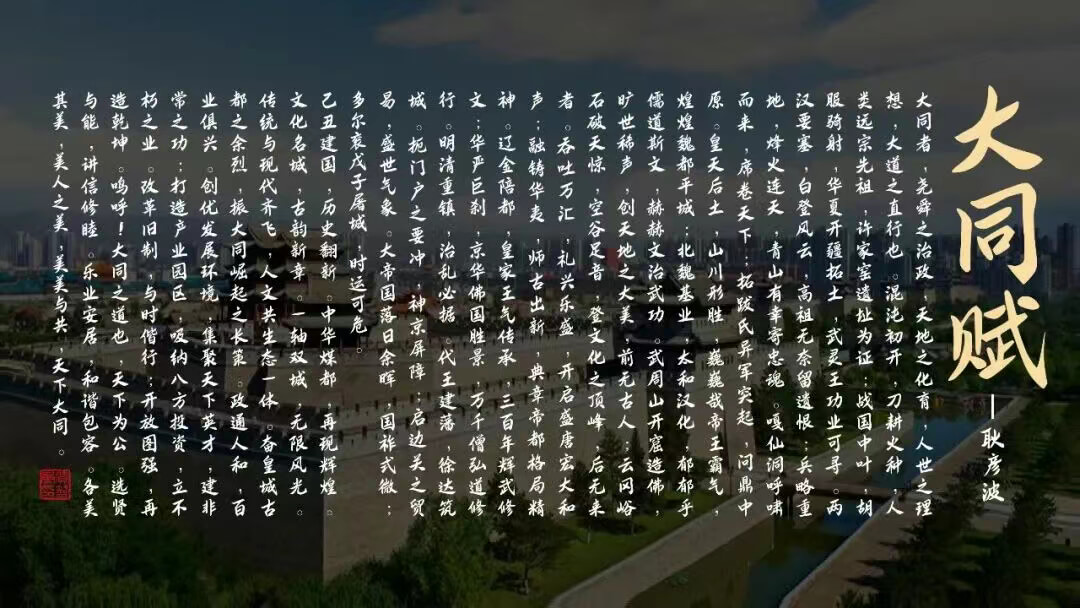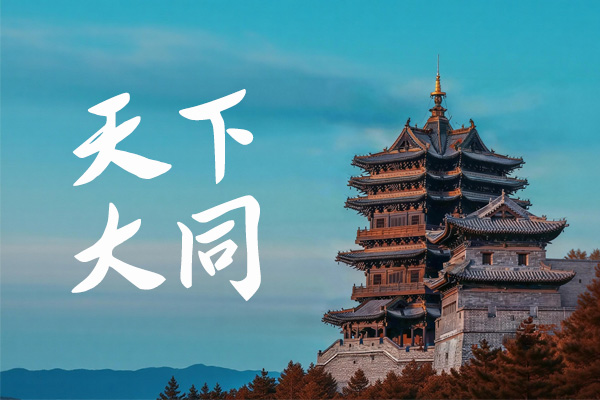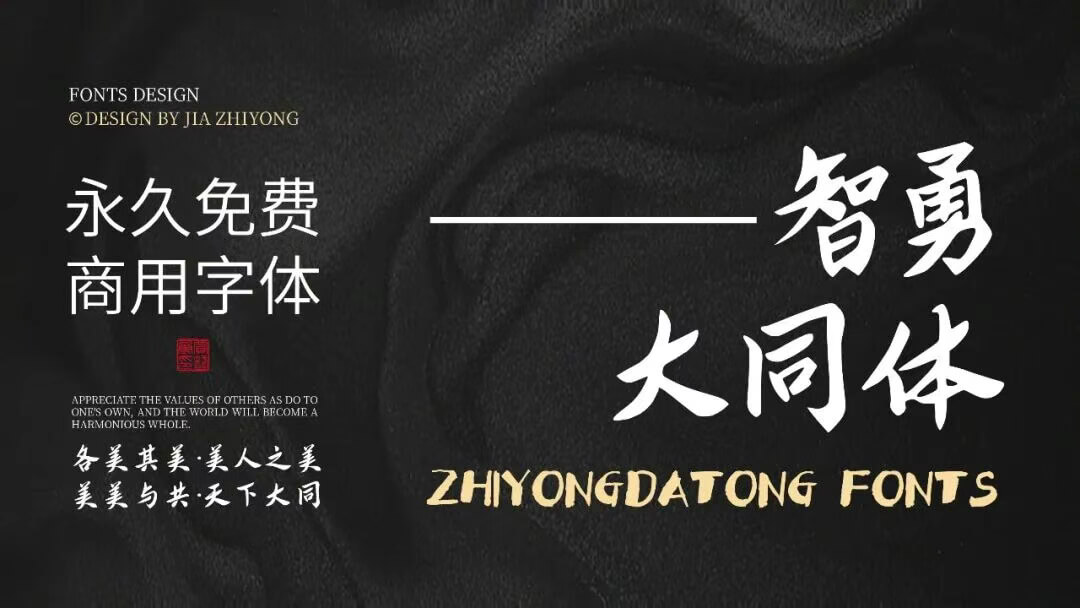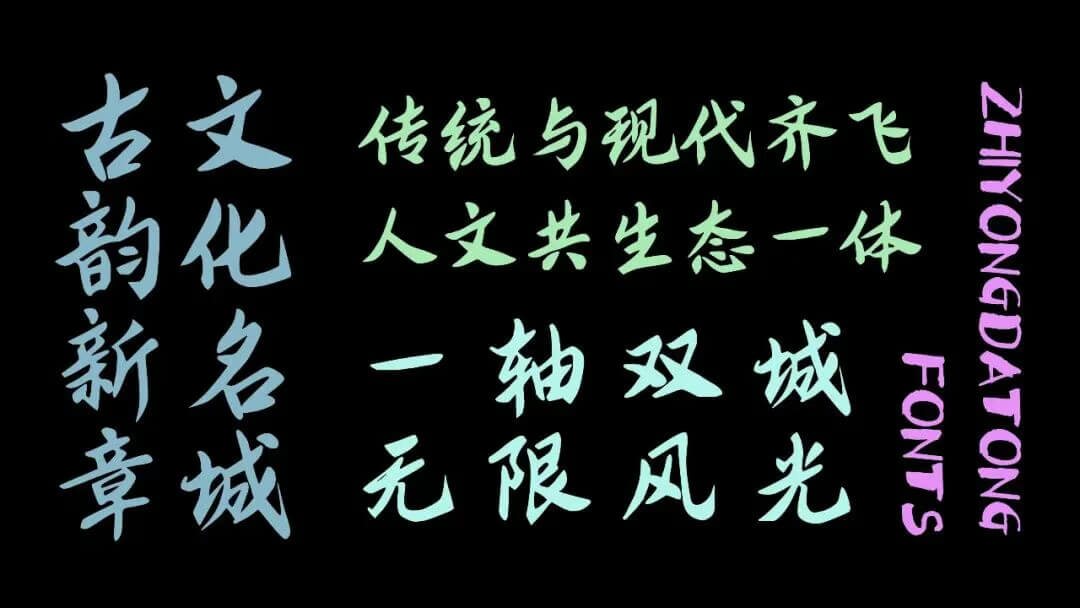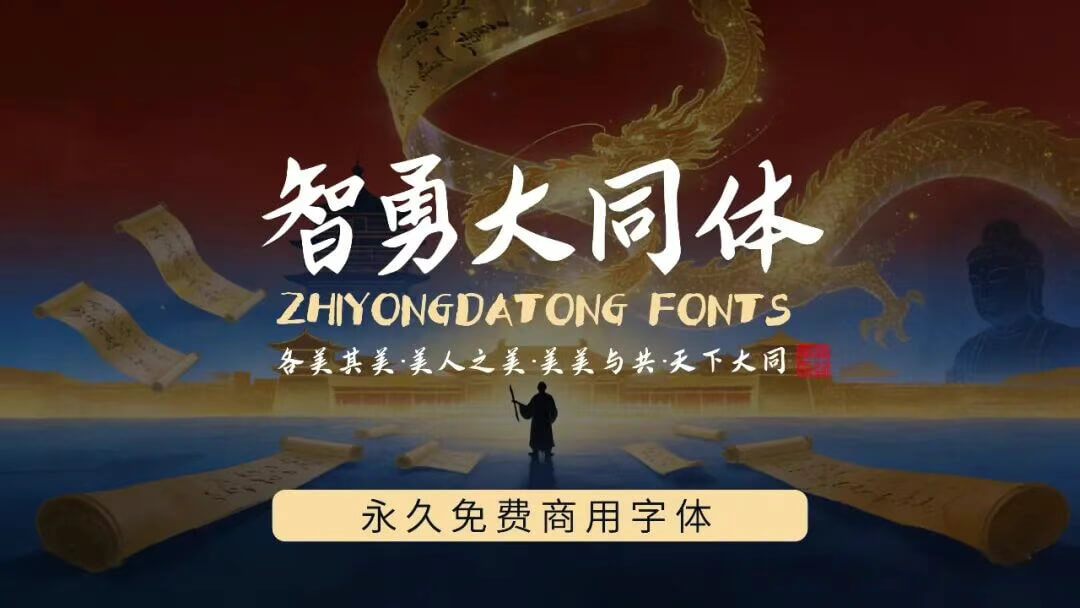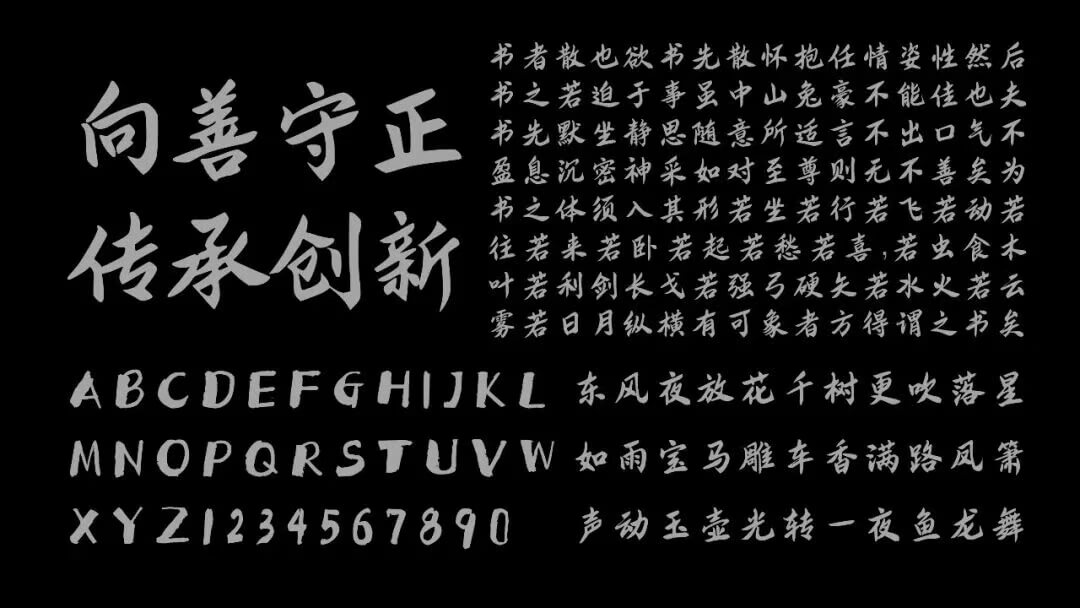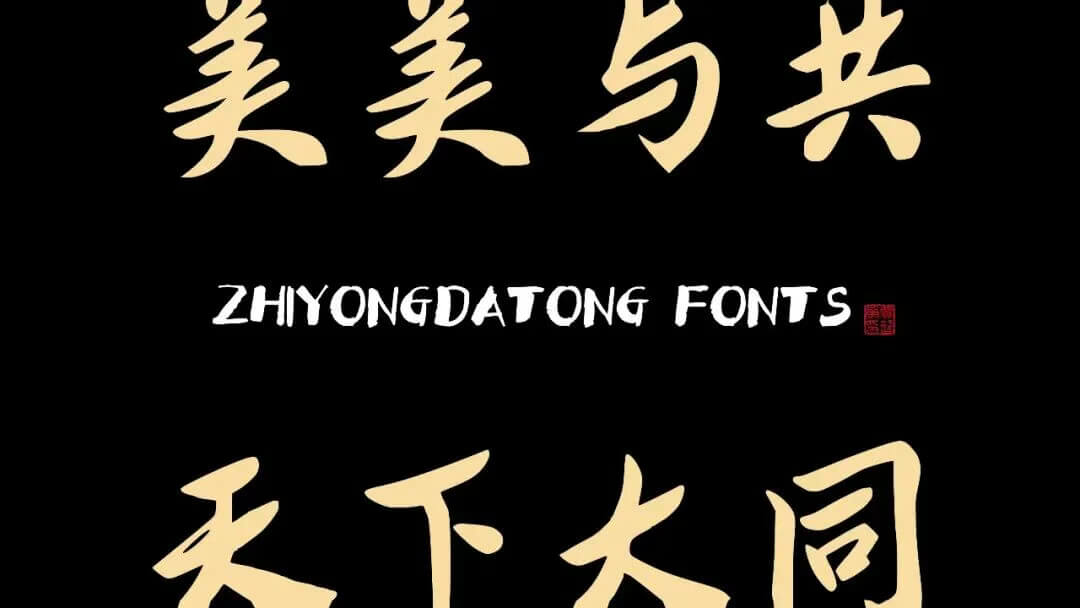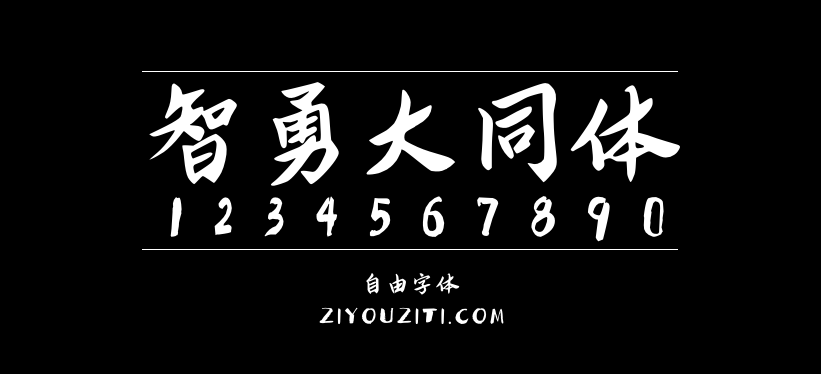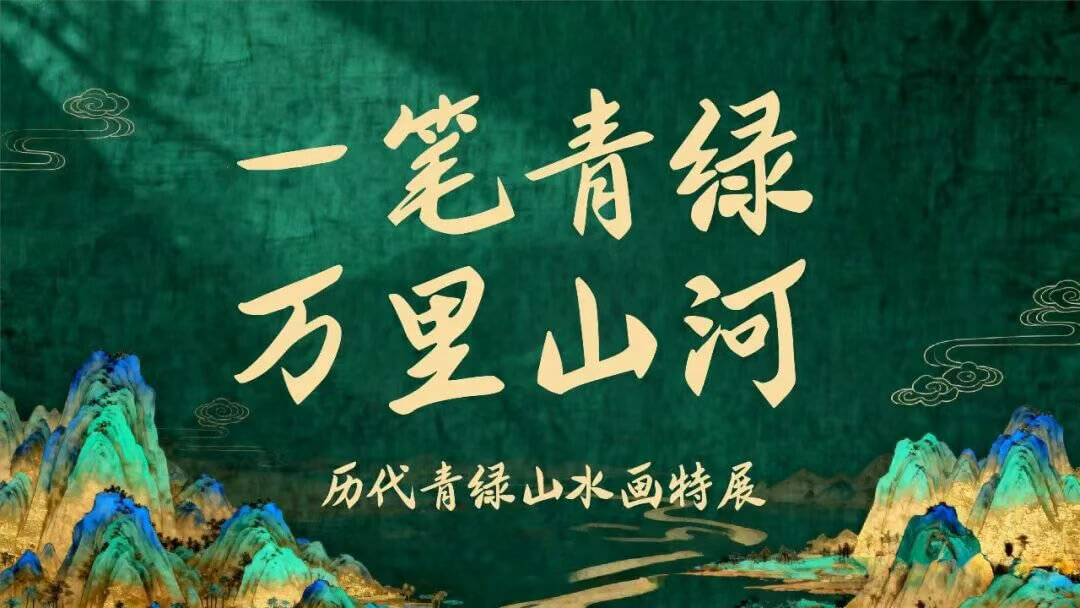
智勇大同体
智勇大同体是设计师贾智勇(智勇造字)创作并推出的第四款免费商用字体,前面三款字体分别是:
一个普通的午后,智勇用毛笔写下第一个字型。那一刻,作者没想到这会成为一场长达两年多的字体之旅。
为了让它真正成为一套能够被大家自由使用、涵盖近万个汉字的完整字库,智勇请来了AI助手,将手写风格延伸、生成。然而,生成不是终点。在之后的漫长时光里,智勇坐在电脑前,对着屏幕上的每一个字,开始了枯燥又必需的“修型”。
历时两年多,6763个常用汉字,从最初的手写草稿,到AI辅助生成的初步字库,再到如今逐字精修的成品,每一个笔画都浸润着作者对家乡的热爱,对字体设计的热爱,以及对“天下大同”理念的执着追求。
字如其名:三重深意
智勇 :是智勇的名字,贾智勇,它代表着这款字体的起点,是作者个人意识与字体的投射。
大同 :智勇的家乡山西大同,这座承载着北魏、辽金等朝代辉煌历史的城市,为我提供了无尽的设计灵感。
大同 :更取“天下大同”之意,各美其美,美人之美,美美与共,天下大同。希望这款免费商用的字体可以为更多人提供设计的温暖与便利,让设计的力量惠及天下。
设计亮点:传统与现代的完美融合
手写温度 :保留了手写体的自然流畅与个性,复古与人文的平衡
AI辅助 :通过AI辅助,确保了字型的规范统一与视觉平衡,让传统手写更具现代感。
逐字精修 :每一个字型都经过反复推敲与调整,力求在美观与实用之间找到最佳平衡点。